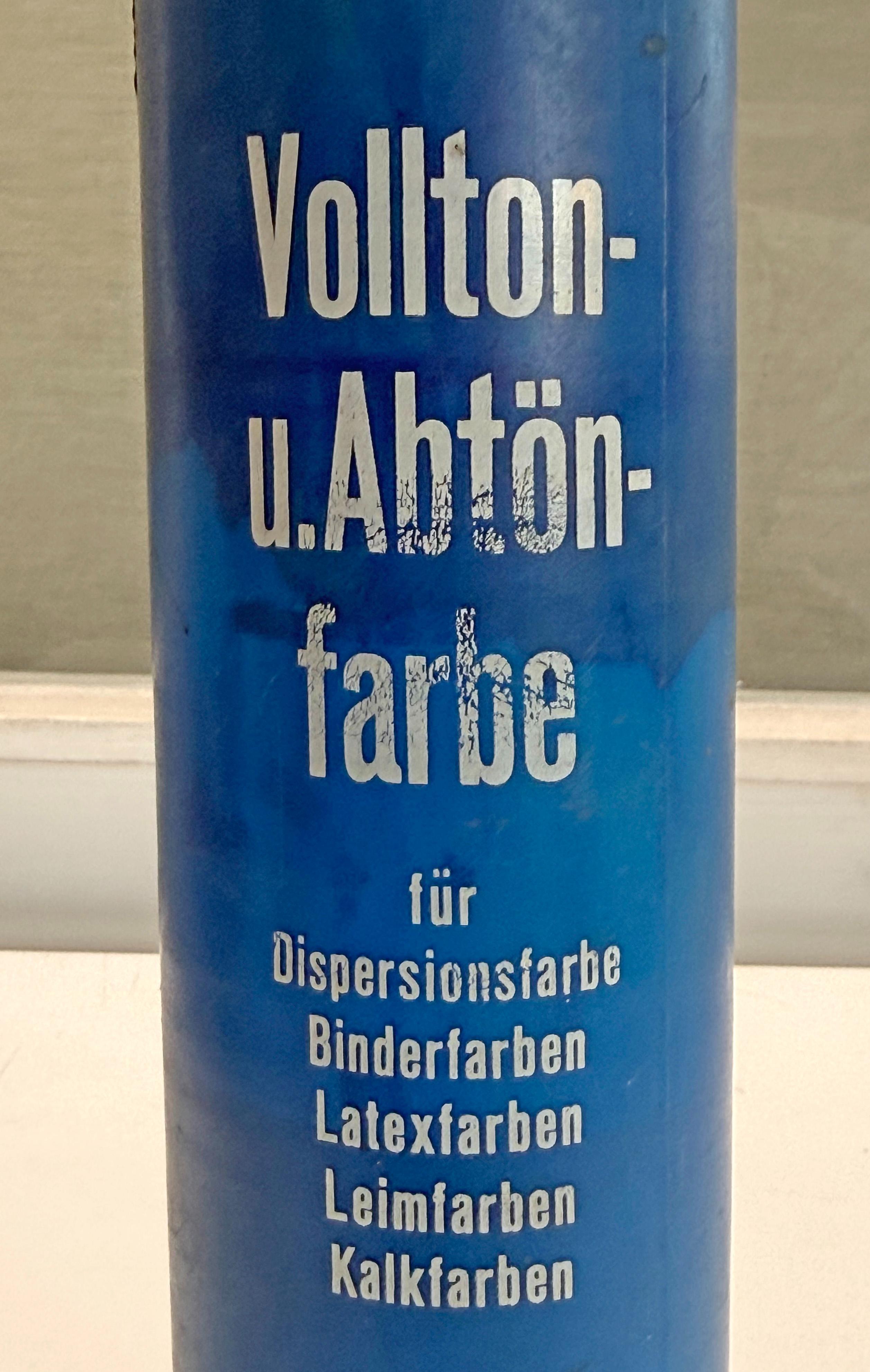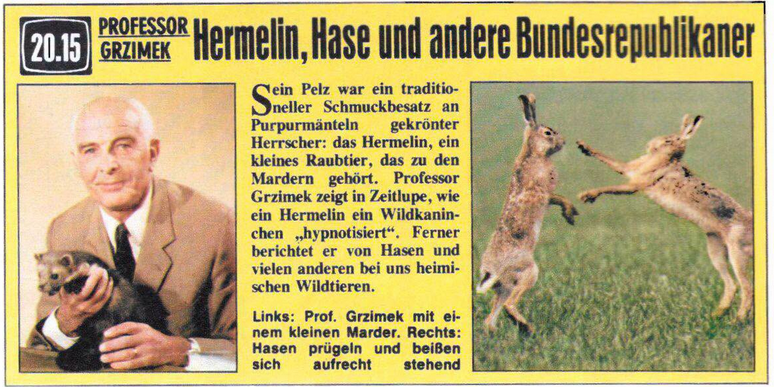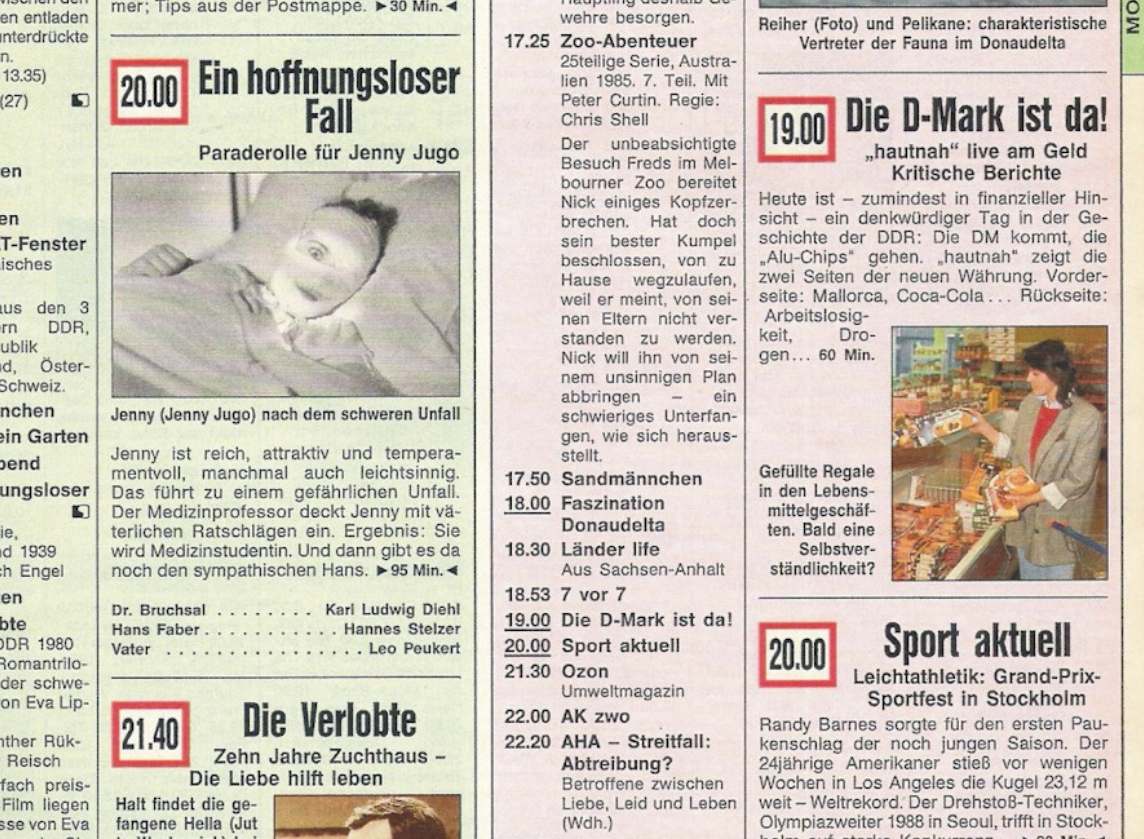
Serifenlose Schmalschrift auf Plastikflasche (70er Jahre)
Auf einer etwas älteren Kunststoffflasche mit blauem Abtönkonzentrat,
die seit den mittleren 70er Jahren bei uns im Schrank steht und nun entsorgt werden soll,
"lächelt" mich seit Jahrzehnten eine schmale serifenlose Schrift an.
Die schrägen An- und Abstriche machen die Type besonders interessant.
Handelt es sich etwa um die Venus?
Was meinst ihr?
Ich bin mit nicht sicher, aber wurde in der Hör Zu (hier eine Ausgabe von 1982) die VENUS nicht auch eingesetzt oder bin ich da blind?
wurde in der Hör Zu (hier eine Ausgabe von 1982) die VENUS nicht auch eingesetzt
Eher nicht, da bei der Hörzu die schrägen An- und Abstriche fehlen.